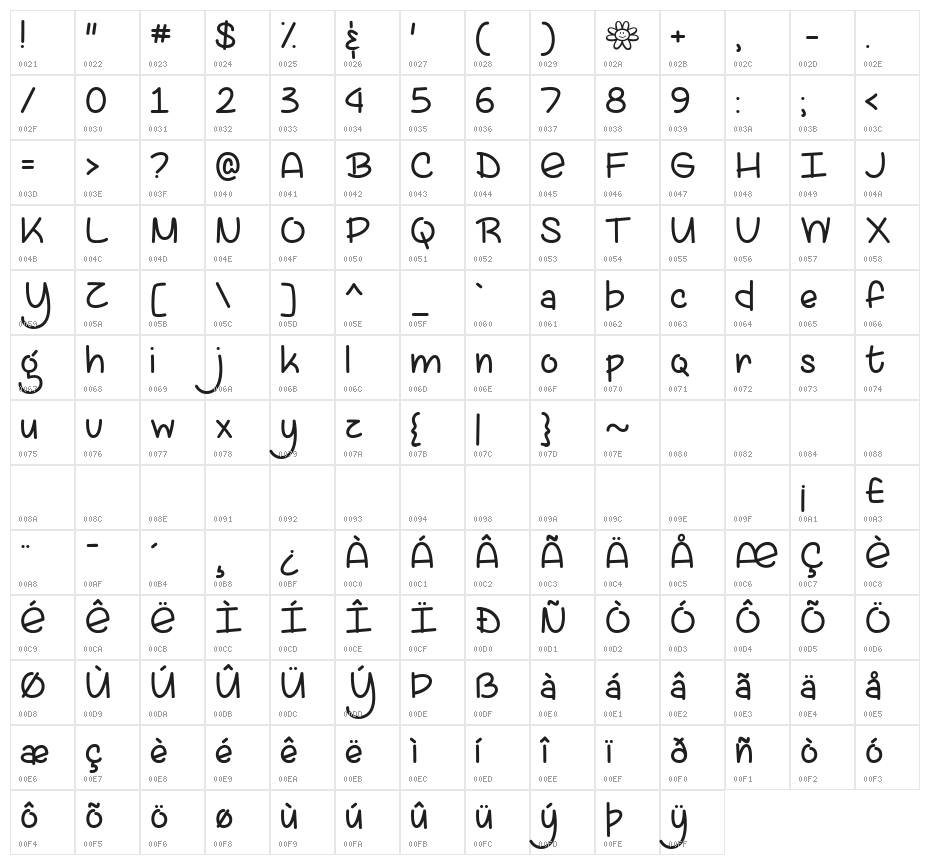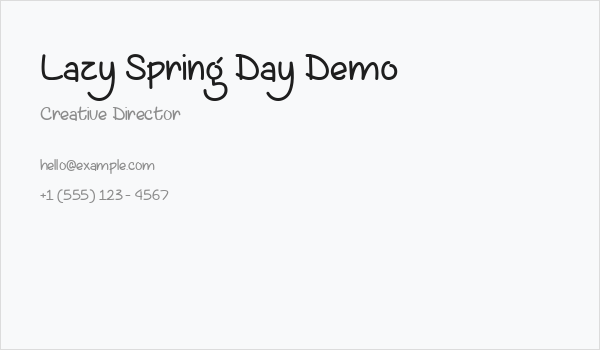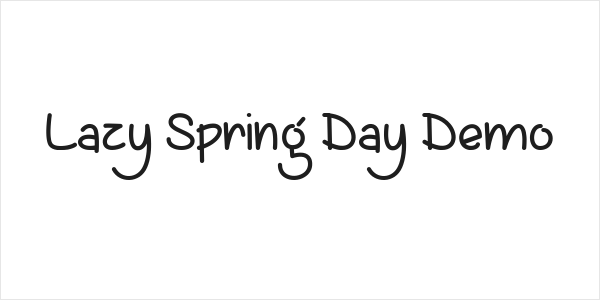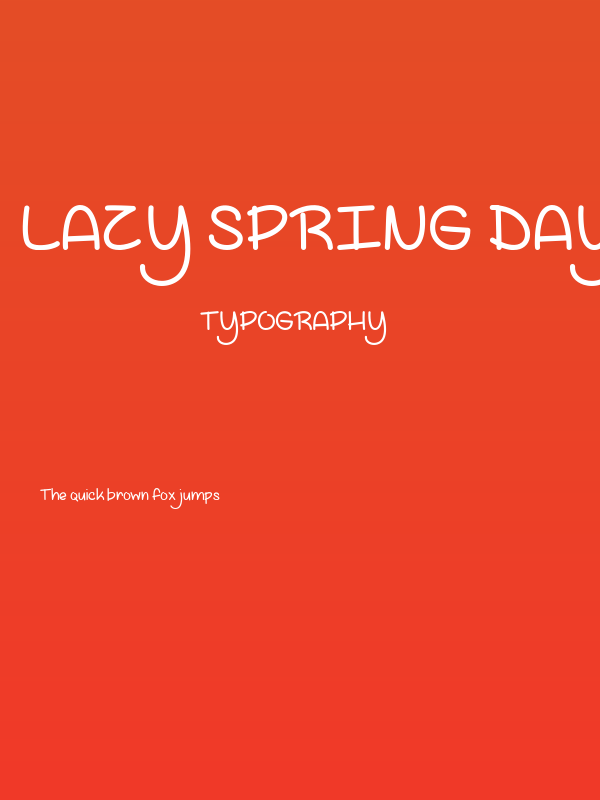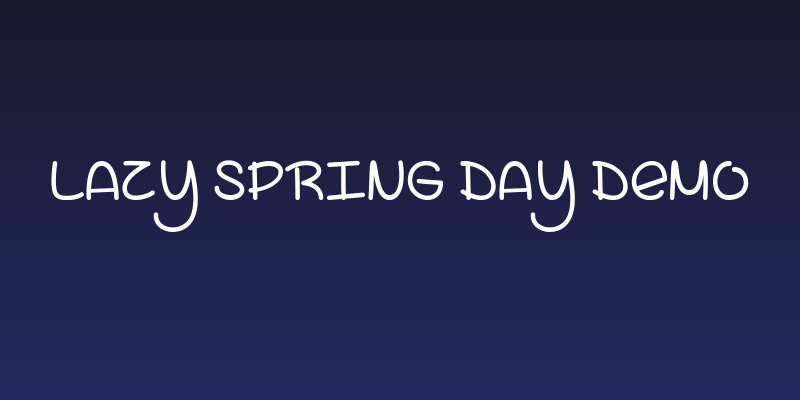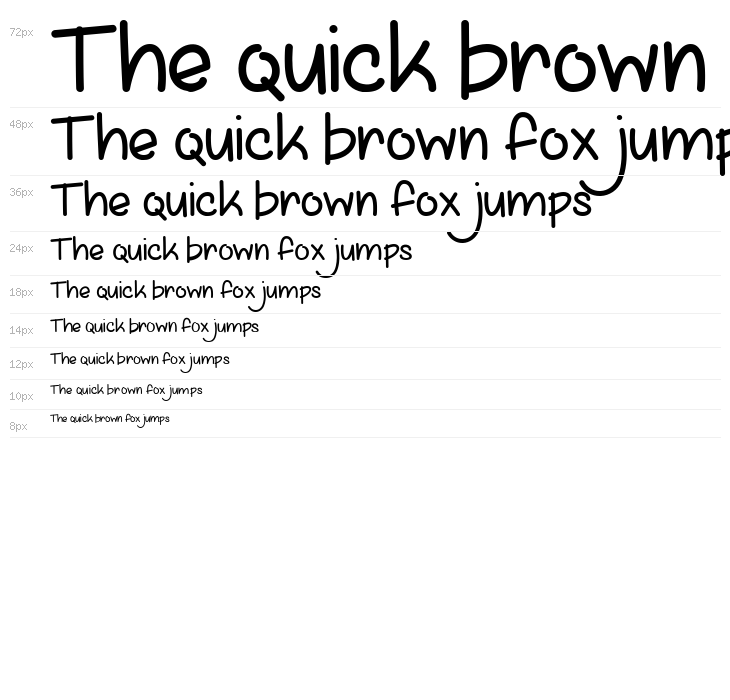
Lazy Spring Day Demo Font
| Stile generale | Casual, Playful |
| Caso d'uso | Headlines, Informal text, Creative projects |
| Progetti proposti | Ideal for children's books, greeting cards, playful branding, and casual invitations. |